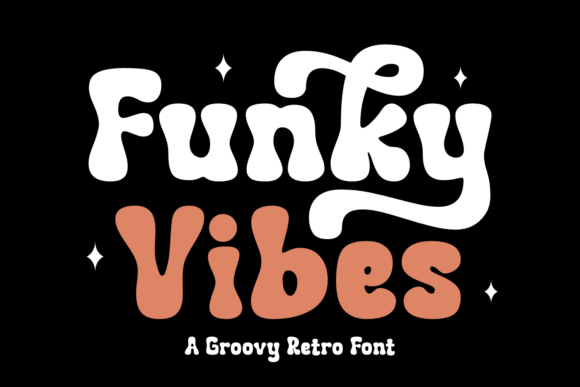
Funky Vibes
Funky Vibes – Review Completa da Fonte Display Mais Alegre do Ano
Se você está em busca de uma fonte display que traga personalidade, alegria e originalidade aos seus projetos, Funky Vibes é a escolha perfeita. Esta tipografia cute e quirky foi criada para quem deseja transformar ideias criativas em peças visualmente impactantes.
Por que escolher a Funky Vibes?
- Design alegre e vibrante – Cada caractere foi desenhado com detalhes divertidos que dão um toque de felicidade instantânea.
- Versatilidade – Ideal para títulos, logotipos, convites, pôsteres, embalagens e até posts de redes sociais.
- Leitura clara – Apesar do estilo descontraído, a fonte mantém ótima legibilidade em diferentes tamanhos.
Como a Funky Vibes pode melhorar seus projetos
Ao aplicar Funky Vibes nos seus layouts, você observará:
- Um impacto visual imediato que chama a atenção do público.
- Uma sensação de modernidade sem perder o charme artesanal.
- Maior engajamento nas redes sociais, já que textos criativos tendem a gerar mais curtidas e compartilhamentos.
- Facilidade de combinar com outras fontes neutras (como Montserrat ou Open Sans) para criar hierarquias tipográficas equilibradas.
Onde usar a Funky Vibes?
- Cartões de convite para festas infantis ou eventos temáticos.
- Branding de marcas que desejam transmitir leveza e diversão.
- Capas de livros, revistas e e‑books voltados ao público jovem.
- Posts de Instagram, TikTok e Pinterest que precisam se destacar no feed.
- Materiais de marketing como flyers, banners e anúncios digitais.